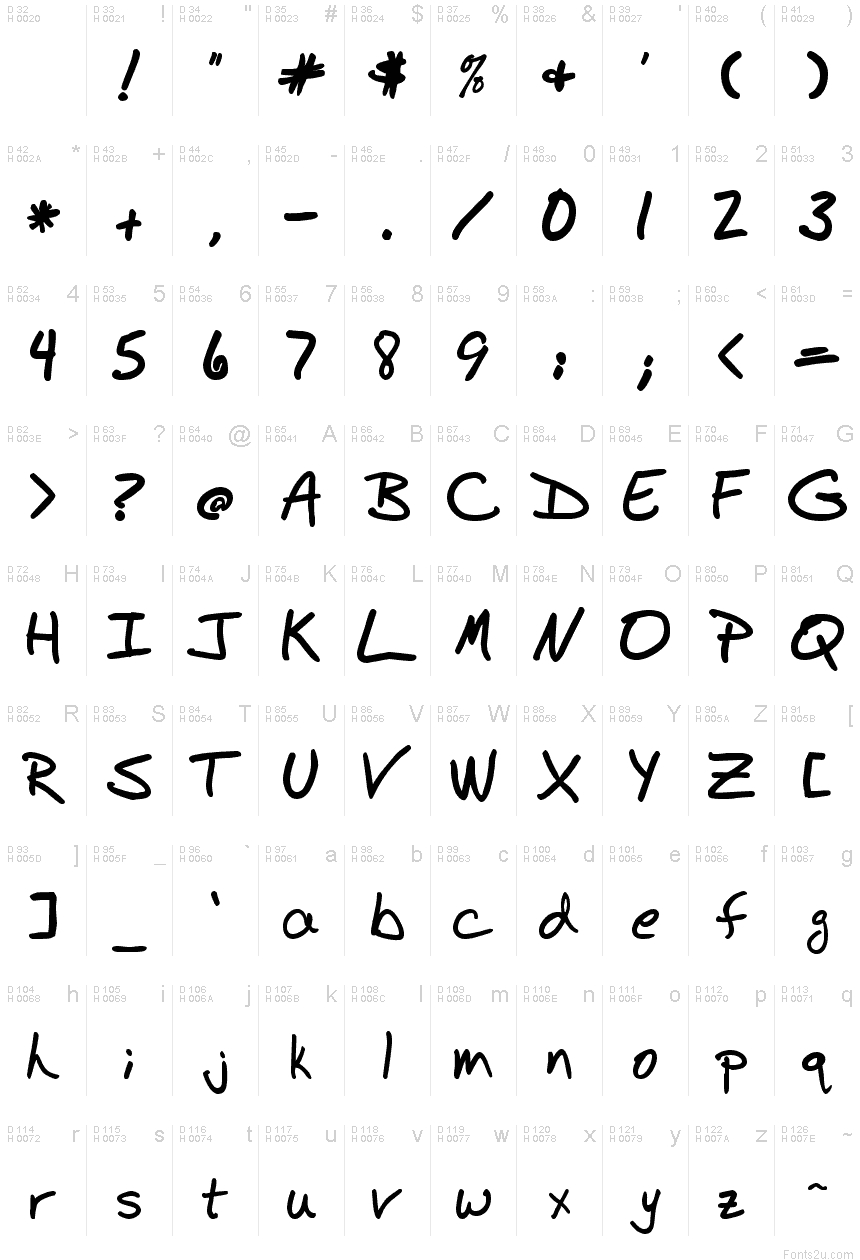
BudHand Bold, autorstwa Johna D. „Buda” Banksa, to darmowy krój pisma odręcznego, który wreszcie trafia w punkt, łącząc przyjazny charakter z czytelnością. Kreski są grube, wyraziste i pewne, a zaokrąglone krzywe sprawiają wrażenie szybkiej notatki napisanej pisakiem, a nie sztywnego cyfrowego efektu. Litery łączą się z łatwością, nadając rodzinie BudHand swobodne, ludzkie ciepło, przy czym całość pozostaje na tyle przejrzysta, że sprawdza się nawet w dłuższych zdaniach i przy mniejszych napisach.
BudHand Bold to darmowy font, który świetnie sprawdzi się na plakatach, w materiałach edukacyjnych, zabawnym brandingu, etykietach, grafikach z cytatami, postach w mediach społecznościowych czy ulotkach, gdzie zależy Ci na charakterze bez zbędnego chaosu. Wyrazista waga czcionki dobrze prezentuje się w dużych rozmiarach, a otwarte kształty znaków zapobiegają zlewaniu się tekstu. Połącz ten darmowy font z prostym krojem bezszeryfowym w tekście głównym, a BudHand wykorzystaj w nagłówkach i akcentach, które mają wyglądać przystępnie i naturalnie.